2023 年のベスト ライトニング フォント 14 選 (無料およびプレミアム)
公開: 2023-09-12あなたは、プロジェクトを次のレベルに引き上げる完璧なフォントを探しているグラフィック デザイナーですか? これ以上探さない! このブログ投稿では、無料とプレミアムの両方で、2023 年のベスト ライトニング フォント 14 個を調査します。
しかし、なぜライトニング フォントなのか疑問に思われるかもしれません。 ライトニング フォントは、デザインに印象的で刺激的な要素を追加し、視覚的に魅力的で記憶に残るものにする素晴らしい方法です。
したがって、感動的なタイポグラフィーでプロジェクトを盛り上げる準備ができている場合は、読み続けてください。
さあ、ライトニング フォントの世界に飛び込みましょう。 この記事では、印象的なスタイルと多用途性を理由に厳選した、2023 年のトップ 14 のライトニング フォントを紹介します。
大胆なポスター デザイン、洗練されたロゴ、ダイナミックな Web サイトのいずれに取り組んでいる場合でも、これらのフォントは間違いなく存在感を主張します。 しかし、それは美しさだけではありません。
ライトニング フォントは、エネルギーと興奮の感覚を伝える能力があることでも知られており、視聴者の注意を引き、永続的な印象を残すのに役立ちます。 さらに、無料オプションとプレミアム オプションの両方を組み合わせることで、誰の予算にも合うものが見つかります。
ライトニング フォントの世界を紹介し、デザイン プロジェクトに与える潜在的な影響を強調したところで、早速 2023 年のベスト ライトニング フォント 14 個を見ていきましょう。
大胆でエッジの効いたスタイルからエレガントで複雑なデザインまで、あなたの創造性を刺激し刺激するコレクションを厳選しました。 これらの素晴らしいフォントを使用して、あなたのデザインを新たな感動的な高みに引き上げる準備をしましょう。
最高のプレミアムライトニングフォント
あなたのデザインプロジェクトに、刺激的なスタイルを加えたいと考えていますか? 私たちが厳選した最高のプレミアム ライトニング フォント以外に探す必要はありません。
視聴者を魅了するこれらの素晴らしい書体を使って、あなたのデザインを輝かせる準備をしましょう。 以下のオプションを検討して、次のプロジェクトに最適な稲妻フォントを見つけてください。
ライトニングボルト
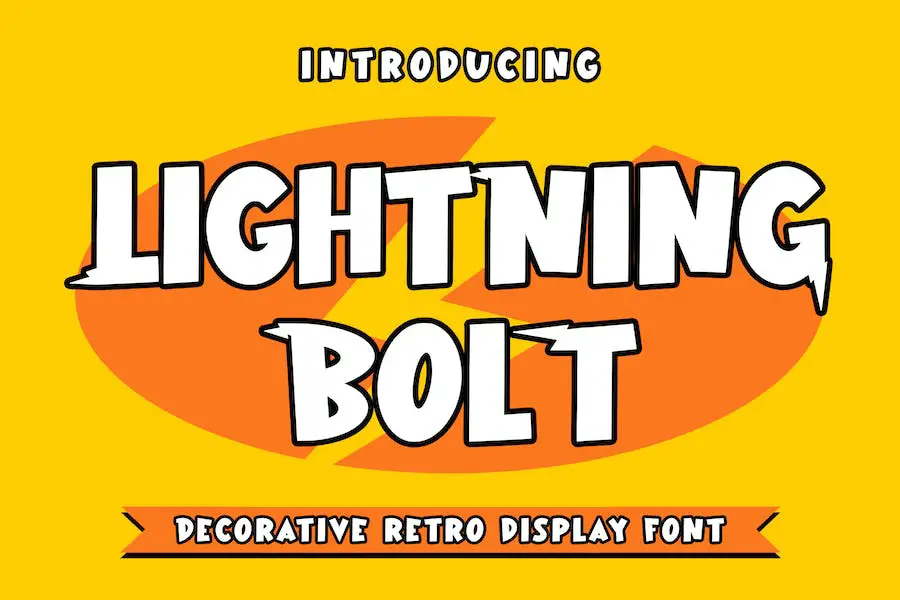
Lightning Bolt は、ユニークな手書き文字を特徴とする装飾的なレトロな表示フォントです。 ブランディング、ロゴ、結婚式、メディア投稿、広告、パッケージ、ラベル、写真、招待状などを含む、さまざまなデザイン プロジェクトに最適です。
このフォントは、手書きスタイルが必要なプロジェクトに個人的で芸術的なタッチを加えます。
嵐
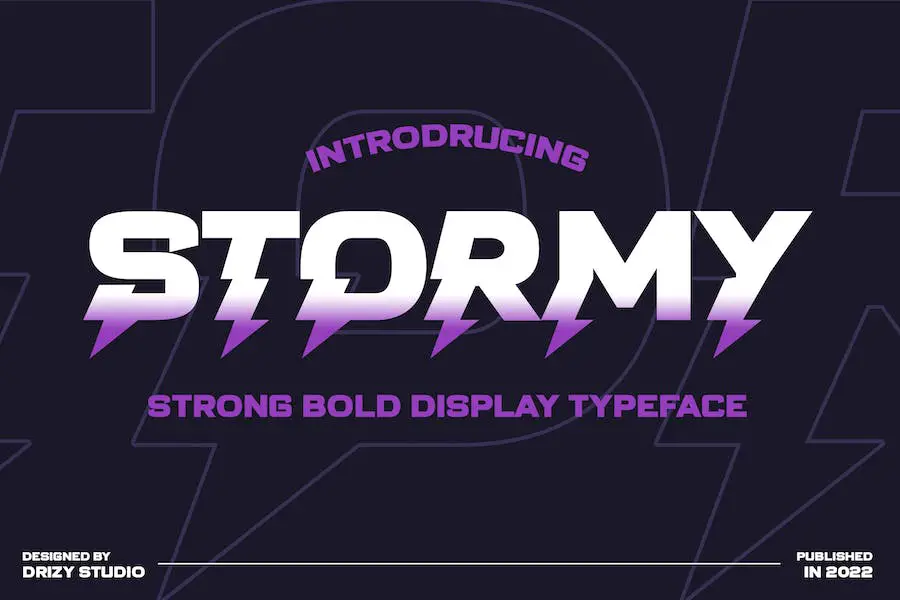
Stormy は、大文字と小文字、数字、句読点、多言語サポート、および合字を提供する電子フォントです。 Drizy Studio によって作成されたこの力強く大胆な書体は、嵐をテーマにしたプロジェクトのデザインを強化するのに最適です。
グラフィック デザイン プロジェクトに取り組んでいる場合でも、Google 向けのコンテンツを作成している場合でも、Adobe でデザインしている場合でも、Stormy はあなたの作品に強力でエッジの効いたタッチを加えます。 Word 文書、Canva デザイン、タトゥー、回路デザインなど、さまざまな媒体で使用できる多用途性を備えています。
サンダーブースト
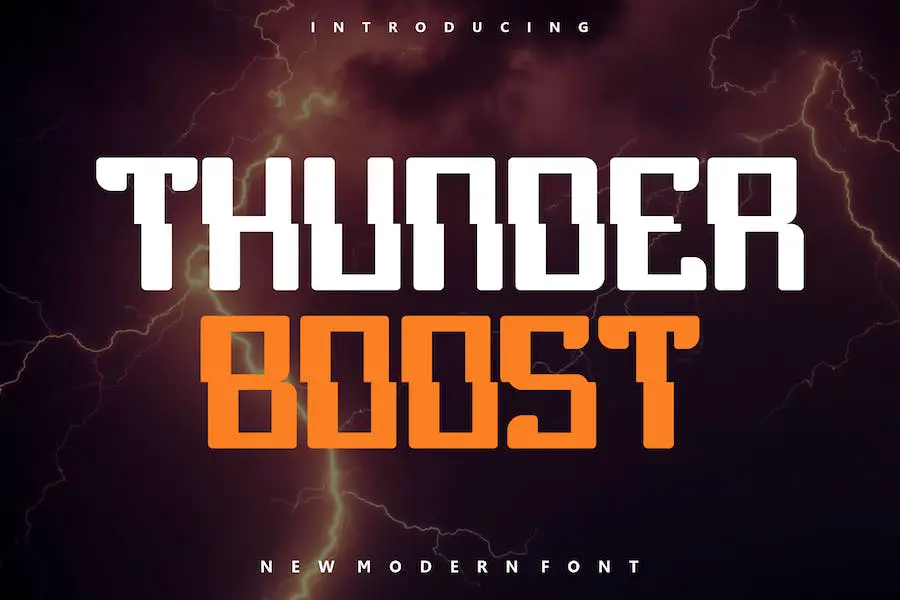
Thunder Boost は、デザイン プロジェクトに大胆さを加える、強力で本格的な表示フォントです。
ロゴ、T シャツのプリント、さらには e スポーツ ブランドに取り組んでいる場合でも、このモダンなフォントはあらゆるブランディング プロジェクトに最適です。 さまざまな状況で目立ち、主張できるため、グラフィック デザイナーにとって多用途の選択肢となります。
ダークサンダー
Dark Thunder は、ラベル、衣類、映画スクリーン、ポスター、映画のタイトル、ライブ、アルバム カバー、ロゴ、その他のクリエイティブ プロジェクトなど、デザインを強化するために設計された独自のフォントです。
このフォントは箱から出してすぐに使用でき、作品に独特のタッチを加えます。 多用途な性質を持つ Dark Thunder は、プロジェクトを次のレベルに引き上げようとしているグラフィック デザイナーにとって必需品です。
稲妻
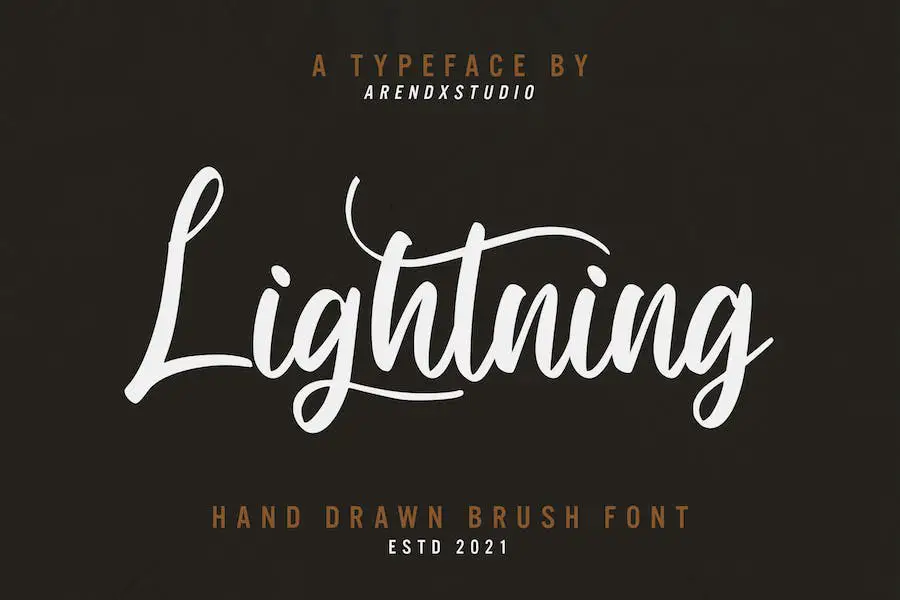
Lightning – Hand Drawn Brush Font は、ユニークな手書き文字を表現する絶妙なフォントで、ブランディング プロジェクト、ロゴ、ウェディング デザインのデザインを強化するのに最適です。
このフォントは多用途なので、メディア投稿、広告、製品パッケージ、ラベル、写真のレイアウト、透かし、招待状、文具などにも使用できます。 手書き要素が必要なプロジェクトに個人的なタッチを加えたい場合は、Lightning が最適なフォントです。
不適合者
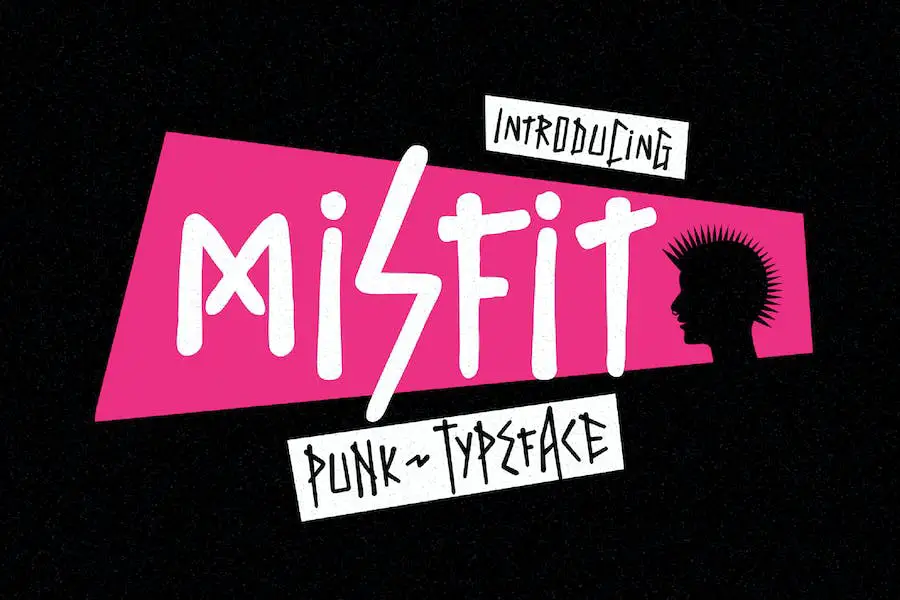
Misfit は、1990 年代のパンク シーンのエッジの効いた雰囲気を伝える書体です。 ポスター、アルバムカバー、アパレル、ロゴなど、さまざまなデザインプロジェクトに使用できる多用途のフォントです。
すべて大文字のスタイルには句読点と数字が含まれているため、小文字と大文字を組み合わせて独自の組み合わせを作成できます。 大胆な主張をしたい場合でも、デザインに反抗的なタッチを加えたい場合でも、Misfit は完璧な選択です。
ショックブロック
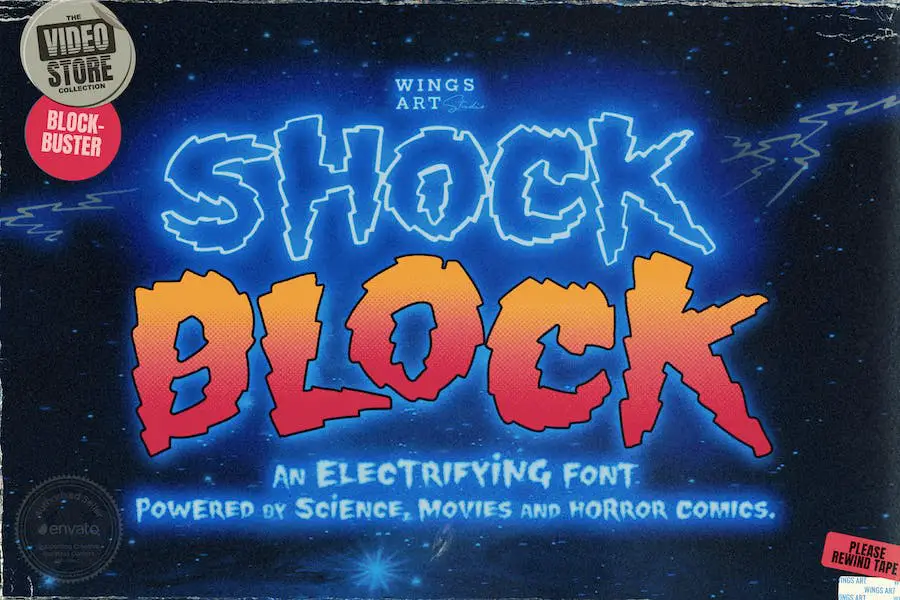
Shock Block は、大文字と小文字を組み合わせたユニークなデザインのオール大文字フォントです。 数字、句読点が付属しており、さまざまな言語がサポートされています。
特徴的なのは、対照的な「ブロック」スタイルと、さまざまな稲妻のシンボルと下線です。 同封の PDF には、ビジュアル内で印象的なエレクトリック ネオンの外観を再現するのに役立つ無料のグラフィック プリセットへのリンクがあります。
このフォントは、映画のタイトル、学校のプロジェクト、プレゼンテーション、漫画、または特別な輝きが必要なあらゆる作品にとって、革新的なフォントです。 そのユニークなスタイルはあなたのデザインを際立たせ、注目を集めます。
ヘリックス
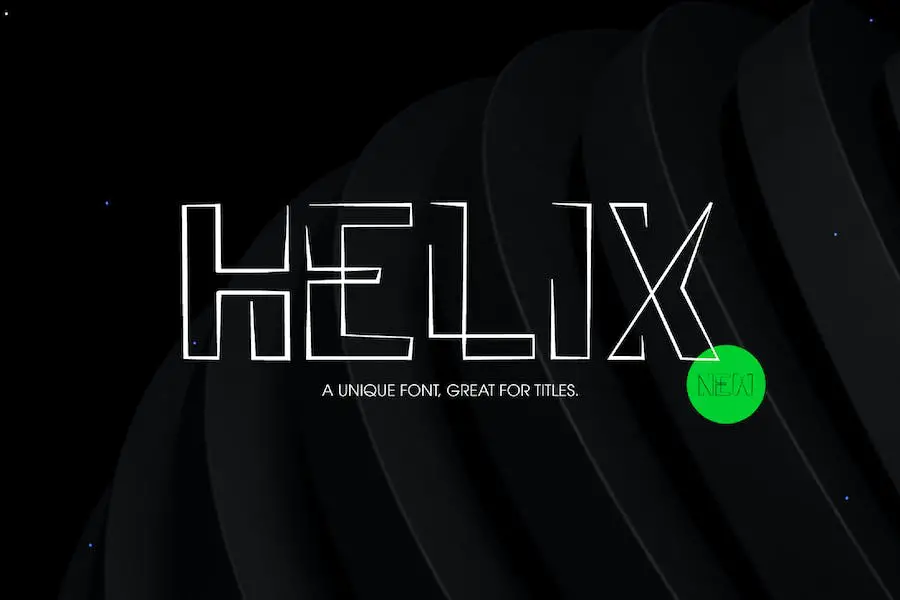
Helix は、デザイン プロジェクトを強化するのに最適な、ユニークな単一行表示書体です。 その目を引くデザインは、確実に主張し、見る人の注目を集めます。
ポスター、社説、見出し、ソーシャル メディアの投稿、パッケージのいずれを作成する場合でも、Helix はあらゆるニーズを満たすのに十分な多用途性を備えています。
Helix の際立った特徴の 1 つは、その珍しい幾何学的なデザインです。 これにより、フォントにモダンでトレンディな外観が与えられ、より伝統的な書体とは一線を画すようになります。 Helix を使用すると、デザインにエッジと洗練のタッチを加えることができます。
もつれ
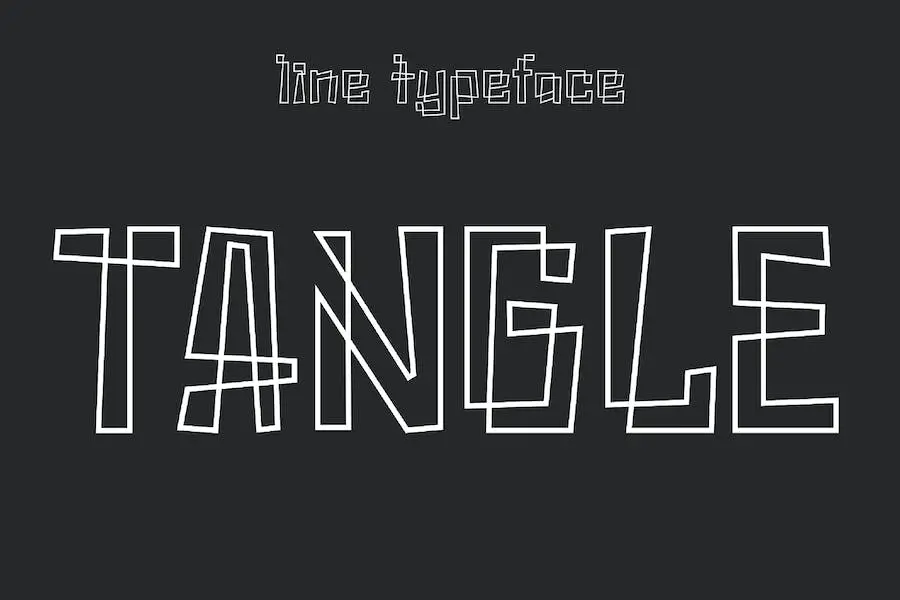
Tangle は、大文字と小文字に加えて、必要な特殊文字をすべて提供する美しいラインアート書体です。 ミニマルでユニークなデザインは、プロジェクトに楽しさを加えます。
ポスター、アルバム カバー、グラフィック デザイン、ソーシャル メディア コンテンツのいずれに取り組んでいる場合でも、このフォントは抽象的で人目を引くものを作成するのに最適です。 雑誌、広告、児童書、ブランディング、パッケージ、文具などにも適しています。
最高の無料ライトニングフォント
あなたのデザインプロジェクトに衝撃的な後押しを加えたいと考えていますか? これ以上探さない! このセクションでは、デザインに強力なパンチを加える最高の無料の稲妻フォントのリストを厳選しました。
これらの素晴らしいフォントをお見逃しなく – チェックして、プロジェクトにふさわしい輝きを与えましょう!
チョピック
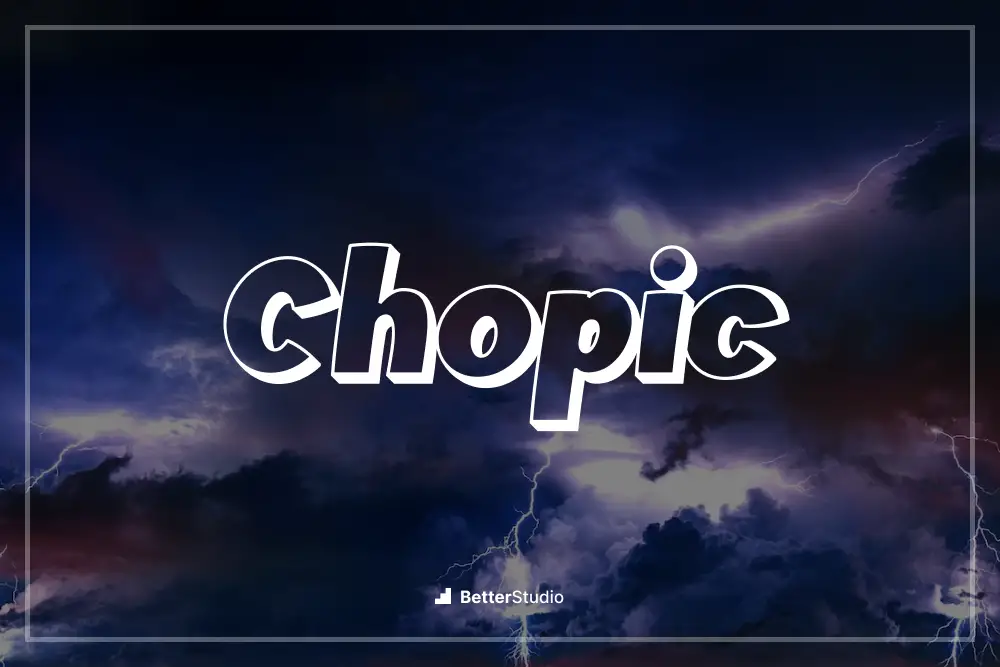
Alit Design の Chopic は、プロジェクトのデザインを強化したいグラフィック デザイナーに最適な 3D フォントです。 Chopic は、ユニークで人目を引くスタイルで、あらゆるデザインに創造性とプロ意識を加えます。
フォントは読みやすく、プロジェクトの視覚的な魅力を即座に高めることができます。 その属性には、テキストに奥行きと立体感をもたらし、目立たせる 3 次元デザインが含まれます。
Chopic は、タイポグラフィーで大胆な表現をしたいデザイナーにとって必須のフォントです。 したがって、デザインを次のレベルに引き上げたい場合は、Chopic を試して想像力を現実化してください。
ハリー・P
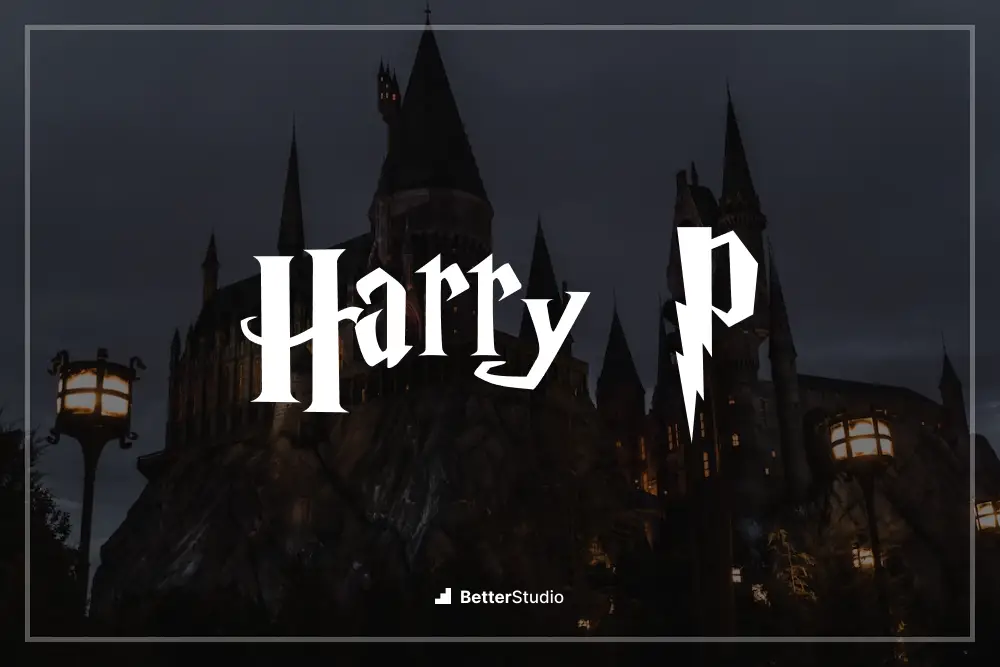
Harry P は、Phoenix Fonts によって作成された素晴らしいフォントです。 そのエレガントでスタイリッシュなデザインは、あらゆるグラフィックデザインプロジェクトの外観を確実に向上させます。 ユニークな特性と多用途性を備えた Harry P は、デザインを次のレベルに引き上げたいグラフィック デザイナーにとって最適な選択肢です。
このフォントは洗練さとプロ意識を醸し出しており、企業のブランディングやロゴに最適です。
すっきりとしたラインと滑らかな曲線が、モダンで洗練された雰囲気を与えます。 パンフレット、ウェブサイト、ポスターのいずれをデザインしている場合でも、ハリー P は高級感とプロフェッショナリズムをさらに加えます。
雷神
God of Thunder は、力強さと大胆さを醸し出すフォントで、あらゆるグラフィック デザイン プロジェクトを向上させます。 JoannaVu によって開発されたこのフォントは、作品に強度とインパクトを加えたいグラフィック デザイナーに最適です。
God of Thunder には、デザインの武器庫に必須のフォントとなるさまざまな属性が備わっています。 その力強く角張った文字の形は注目を集め、鋭いエッジと滑らかな曲線の組み合わせが魅惑的な視覚体験を生み出します。
ポスター、ロゴ、Web サイトのいずれで作業している場合でも、このフォントを使用すると、あなたのデザインが他より目立つようになります。
サンダータイタン
Thunder Titan は、デザイン プロジェクトを次のレベルに引き上げる、強力で印象的なフォントです。 Iconian Fonts によって作成されたこのフォントは、作品に大胆でダイナミックなタッチを加えたいグラフィック デザイナーに最適です。
Thunder Titan を使用すると、デザインを目立たせる、目を引く見出しや注目を集めるタイポグラフィを作成できます。 このフォントの力強くドラマチックな文字の形は、見る人を瞬時に魅了し、忘れられない印象を残します。
結論
要約すると、この記事では、2023 年のベスト ライトニング フォント 14 個を無料とプレミアムの両方で検討しました。 グラフィック デザイン プロジェクトを向上させるために適切なフォントを選択することの重要性について話し合い、検討できる素晴らしいフォントを幅広く提供しました。